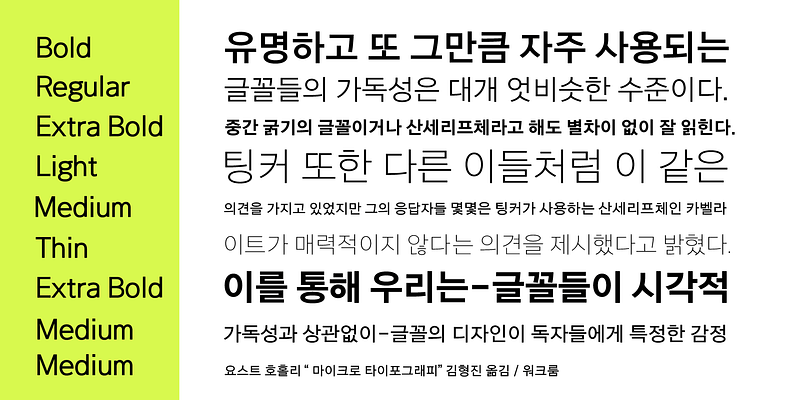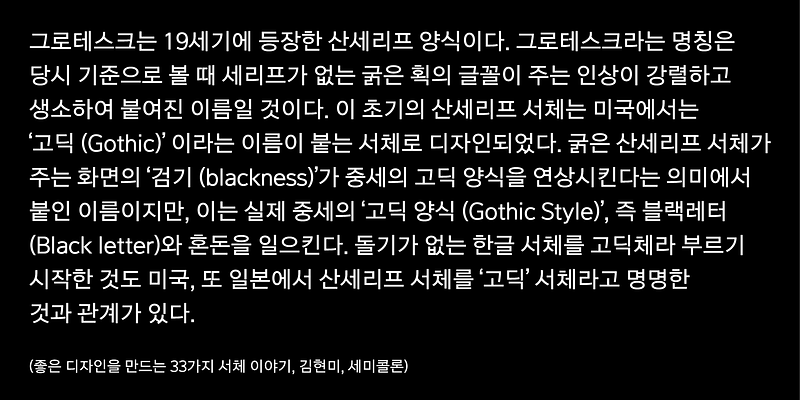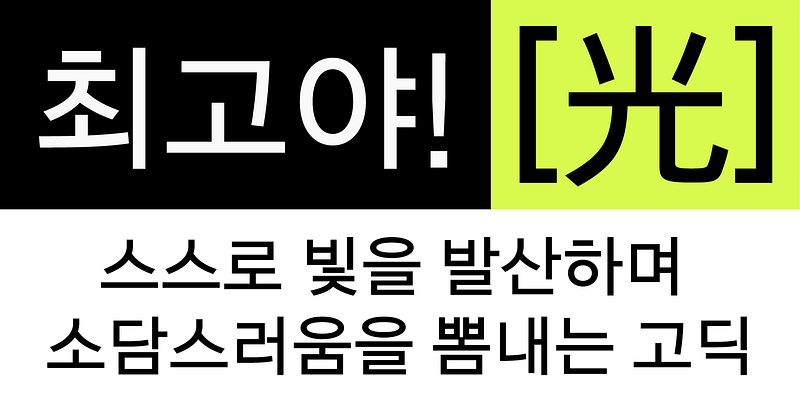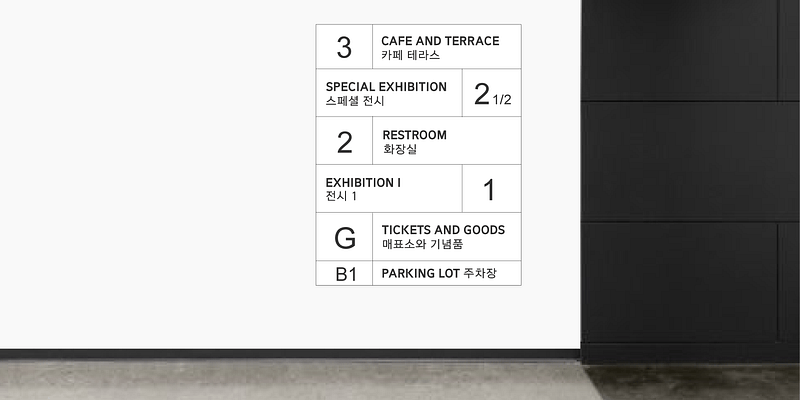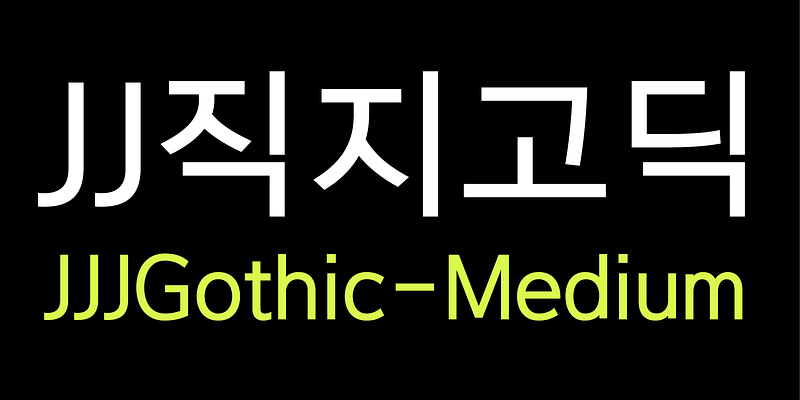
JJJGothic은 산세리프 글꼴을 바디 카피에 사용하는 사용자의 다양한 환경을 분석하여 최적의 간격과 공간 배치를 통해 심미성과 기능성을 극대화하는 데 중점을 둔 서체입니다. 텍스트 서체의 친숙성과 가독성을 최우선으로 합니다. ㅅ,ㅆ,ㅈ,ㅊ에서 떨어지는 획의 형태는 일반적인 대칭 표현이 아닌 비대칭 형태로 차별화됩니다.